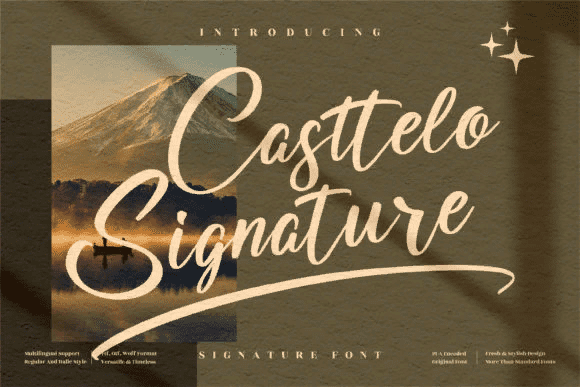
Casttelo Signature
кажется невероятно элегантным и плавным.
Он потрясающе смотрится на свадебных приглашениях, благодарственных открытках, цитатах, поздравительных открытках, логотипах, визитных карточках и любом другом дизайне, требующем рукописного штриха. Он имеет изменяющуюся базовую линию, плавные линии, великолепные глифы и потрясающие чередования.